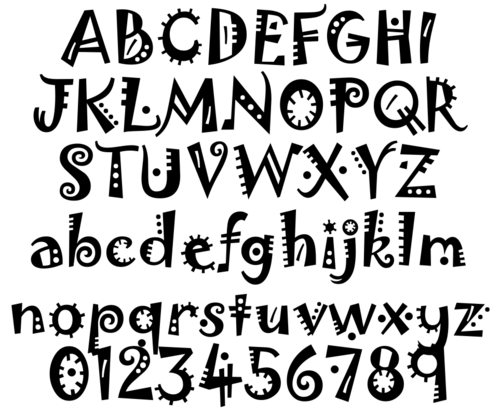
جوكرمان (نوع الخط)
جوكرمان هو خط زخرفي ابتكره المصمم البريطاني أندرو ك. سميث عام ١٩٩٥. [ ١ ] يستخدم هذا الخط نقاطًا ودوامات وخطوطًا مستقيمة يمكن إضافتها أو وضعها بالقرب من كل حرف، أو دمجها في الحرف نفسه لخلق مساحة سلبية . وتصفه مايكروسوفت بأنه يحتوي على "عناصر داخلية وخارجية مميزة". [ ٢ ] وقد أطلق سميث على هذا الخط اسم أغنية بوب ديلان " جوكرمان ". [ ٣ ]
أصدرت شركة International Typeface Corporation نوعين من خطوط جوكرمان: جوكرمان وجوكرمان هيلينيك . يتضمن جوكرمان هيلينيك رموزًا للأبجدية اليونانية . [ 4 ]